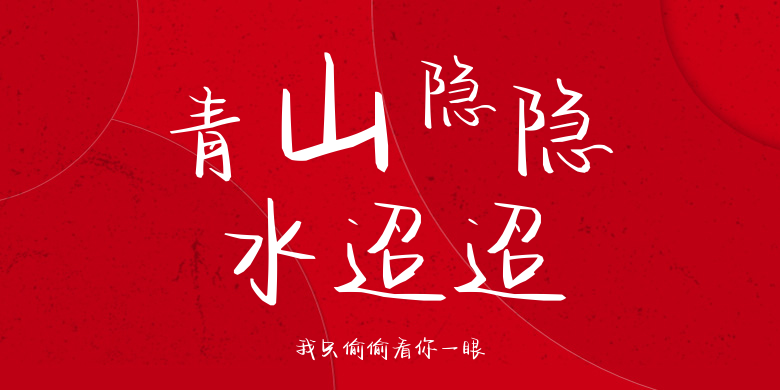
我只偷偷看你一眼
我只偷偷看你一眼,这款字体结构工整、笔画清晰,兼顾美观与易读性,适用于标题、正文、海报、包装、LOGO 等多种场景。字形优雅稳定,风格百搭耐看,适配日常排版与创意设计,让文字呈现更舒适、更具质感。我只偷偷看你一眼一笔一画,皆是细节,以均衡的比例、流畅的线条打造舒适视觉体验,字形端正大气,风格简约现代。无论是商业设计、品牌宣传还是日常排版,都能轻松驾驭,让文字更有格调与力量。我只偷偷看你一眼字体下载。